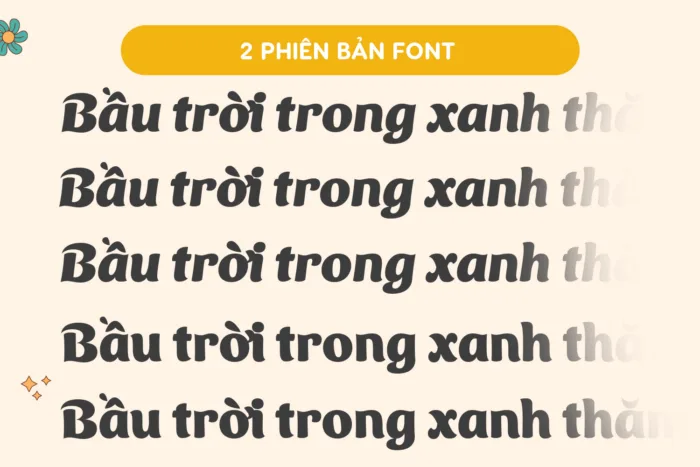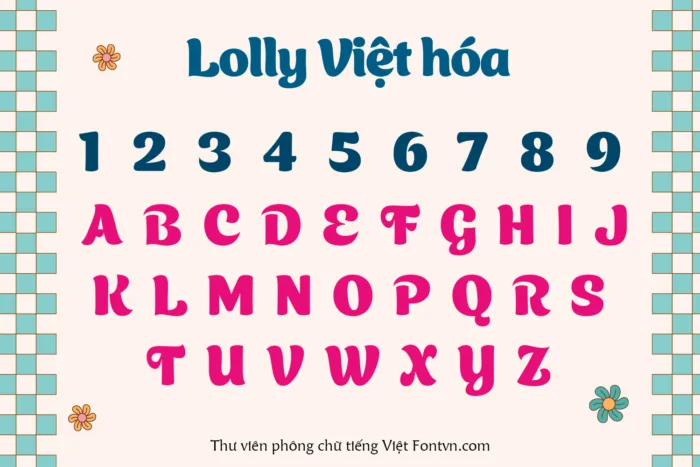
DVN Lolly Việt hóa – Font chữ vui tươi và sáng tạo (2 Style)
DVN Lolly là một kiểu chữ hiển thị mang phong cách tròn trịa, tươi sáng và dễ thương – như viên kẹo ngọt đầy màu sắc trong ký ức tuổi thơ. Với các đường nét mềm mại, bo cong và giàu tính biểu cảm, font mang đến cảm giác gần gũi, ấm áp nhưng vẫn rất hiện đại và linh hoạt trong sử dụng.
Lấy cảm hứng từ những bảng hiệu retro, bao bì bánh kẹo, và không khí lễ hội, DVN Lolly được thiết kế để truyền tải niềm vui, sự sáng tạo và tinh thần lạc quan trong từng con chữ. Dù là dùng trong thiết kế dành cho trẻ em, poster sự kiện, bao bì sản phẩm hay trích dẫn truyền cảm hứng, font đều giúp thu hút ánh nhìn và gợi nên cảm xúc tích cực.
Đặc điểm nổi bật:
Nét chữ tròn trịa, dày dặn nhưng vẫn mềm mại
Phù hợp cho tiêu đề, branding sáng tạo, thiết kế giải trí
Gợi nhớ đến phong cách retro và thiết kế mang tính nghệ thuật
Đem lại cảm giác thân thiện, đáng yêu và tươi mới
Phiên bản đã được việt hóa hoàn chỉnh gồm 2 style: Regular và Italic